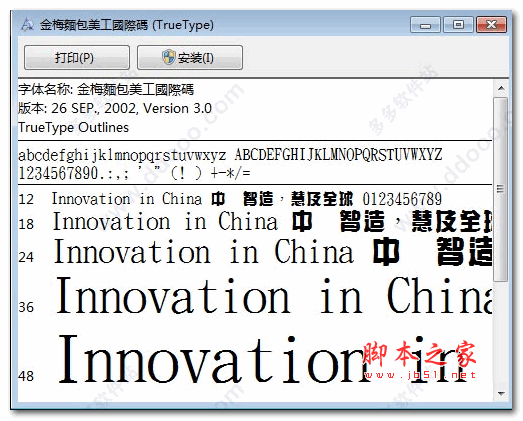
金梅面包美工國際碼是一款適用性非常廣泛的中文字體,該字體端正大方得體,其線條粗細(xì)適中,整體效果出色,能夠應(yīng)用于文本裝潢、信息展示、網(wǎng)頁設(shè)計、篆刻制模、數(shù)據(jù)制作、裝潢設(shè)計、計算藝術(shù)設(shè)計、視覺設(shè)計、字帖等一切合法應(yīng)用場景,有喜歡的朋友可免費下載收藏。